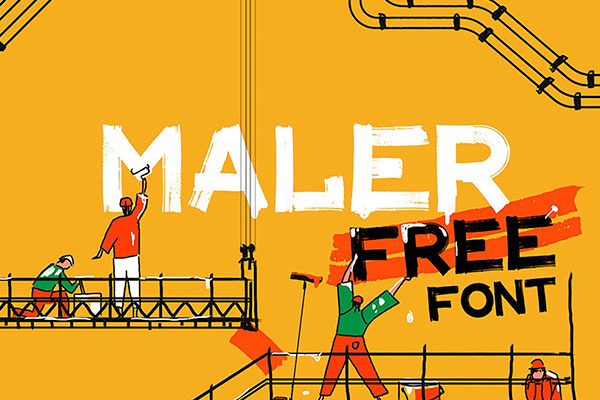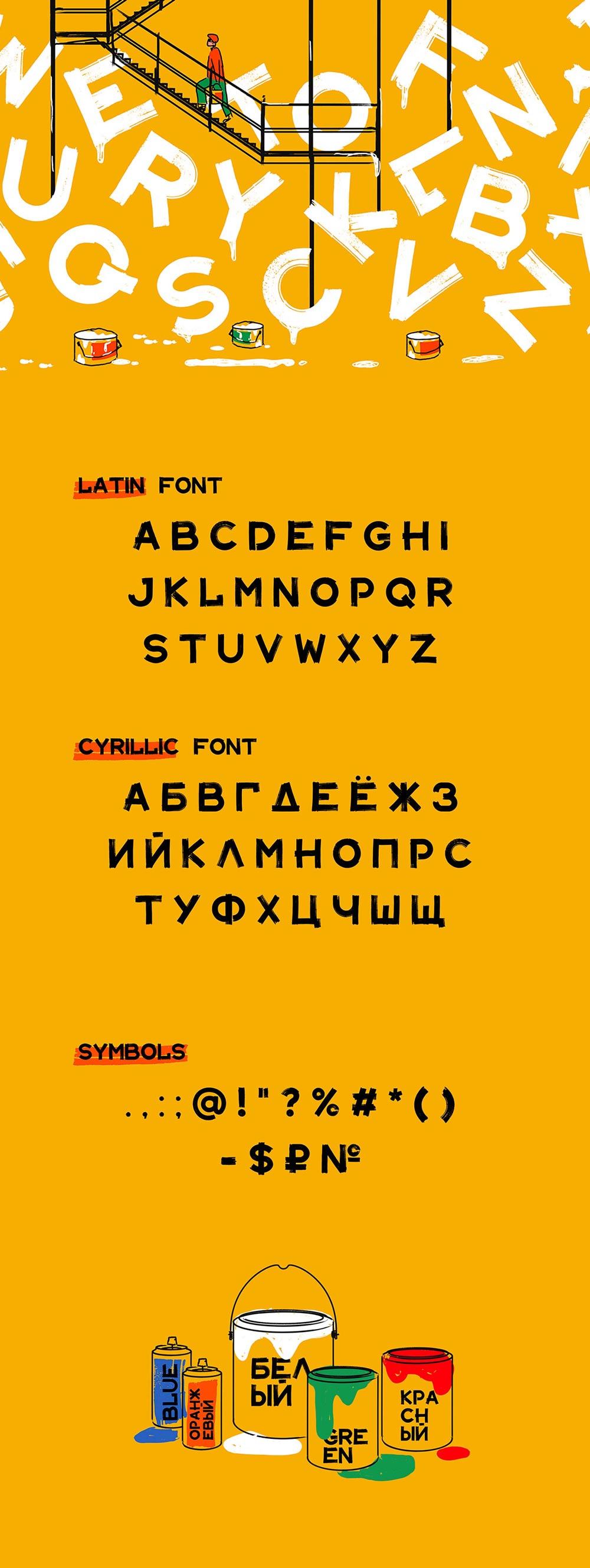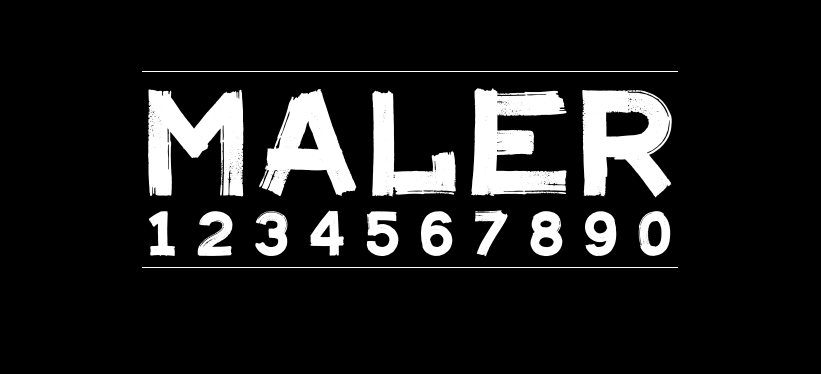
MALER
MALER字体介绍
MALER英文字体来自俄罗斯的MIR设计工作室,它支持拉丁字母和西里尔字母,以便您共享徽标,标题,标题,引号等时,可免费用于您的设计不受任何限制。MALER字体带有油漆刷子的质感,友好且简单,它提供了适合所有年龄段的休闲效果,这意味着您可以使用它来装饰笔记本封面或漫画或为企业创建品牌介绍。它不完美的笔触结合在一起,可以带来轻松的阅读体验,并且除了符号之外,其字母的真实感觉也将成为您添加到每个项目中的一部分。请记住,Maler可用于个人和商业用途,您只需单击一下鼠标,即可为每个键入的字符提供出色的设计。
MALER字体应用示例